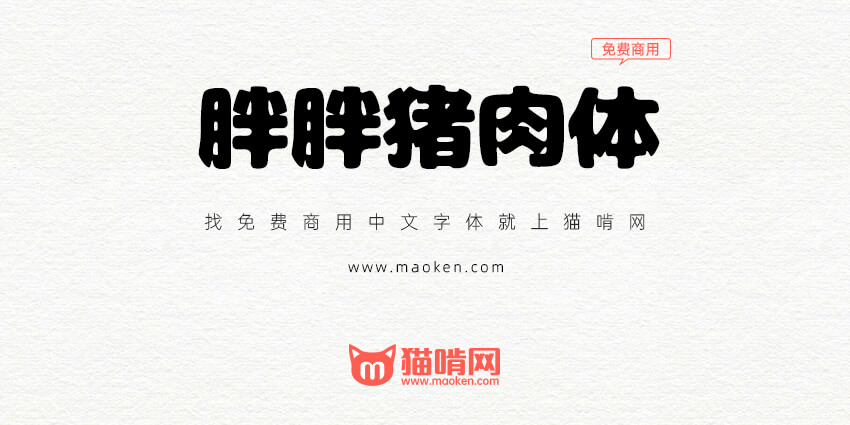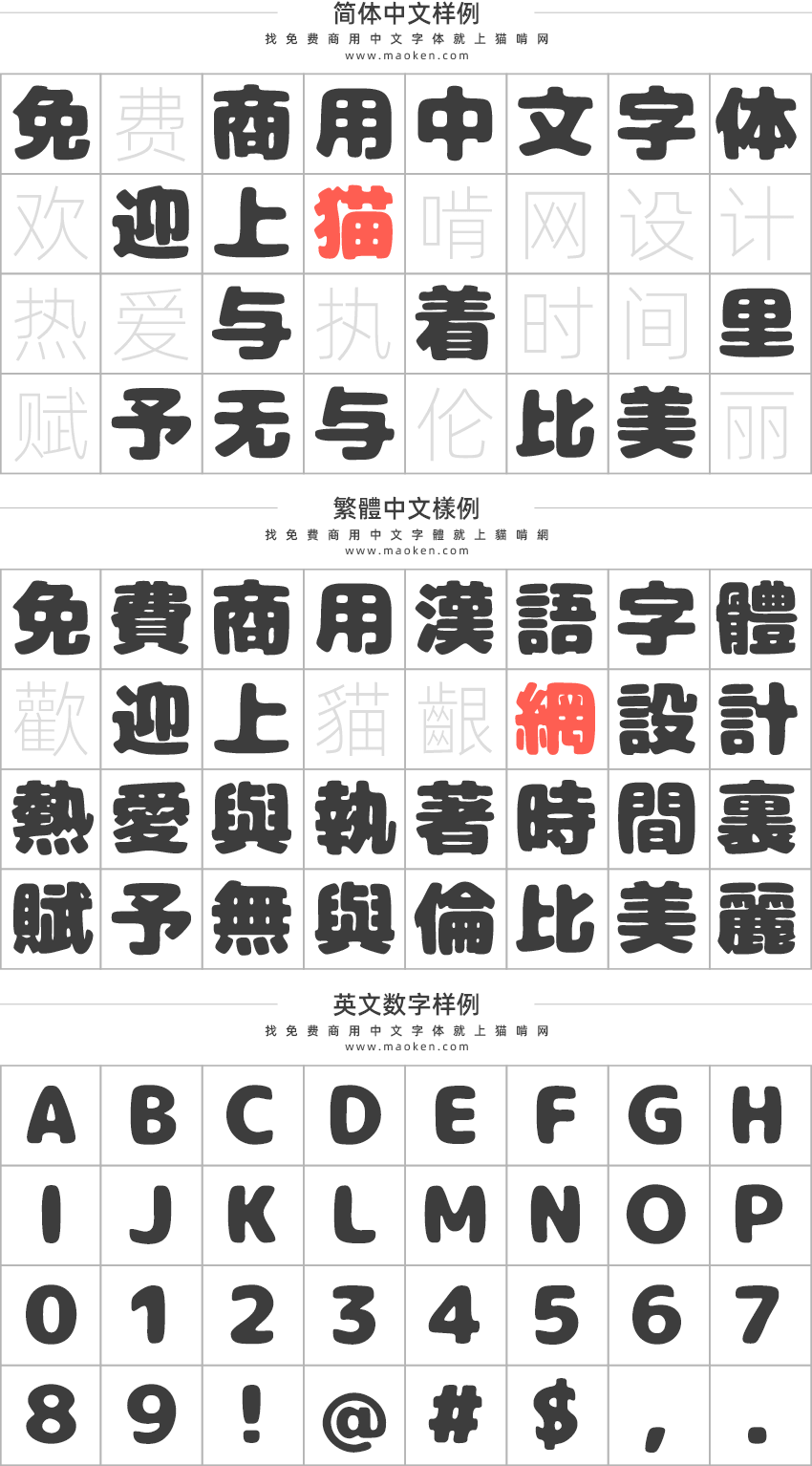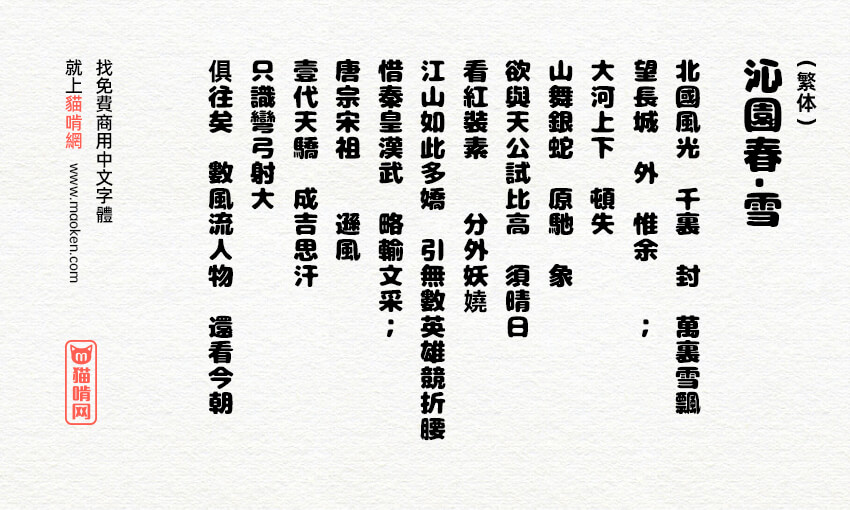
胖胖猪肉体:胖乎乎圆滚滚的可爱日系字体
字体作者:フォントな自由 (其他语种) 字体字重:1个
字体名称:胖胖猪肉体(日文名: にくまるフォント )PS中字体名称:07にくまるフォント Regular
胖胖猪肉体 (日文名: にくまるフォント ) 是一款胖乎乎圆滚滚的可爱日系字体,是基于M+ FONTS进行改造制作而成的字体。这款字体包含日本JIS第1水准2965字,第2水准3390字。简体字符相对较少,繁体字符比较多。
很好的字体,可惜字体不全
如果有人真的,能基于这个字体增补就好了,毕竟想用这种风格的字体哦,就必须购买付费字库,这个字体质量挺可以的啊
这字体是基于M+ FONTS作了整体变形,须原作者公开变形参数,才能对上游M+ FONTS增补简体中文,再应用变形,迄今没有补整体变形后的汉字字体先例,不信可以试试,亲自试了便知为什么不行
• 我不太理解你的意思,建议把这个字体修改,这个字体真适合做一个标题的中文字体,可惜字形不对,有谁能增补和修改一下就好了
非常好的字体,如果谁能基于这个字体增补一下,并且修改一下字形就好了